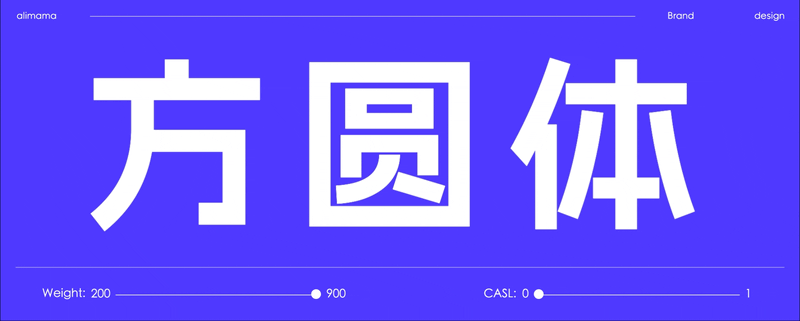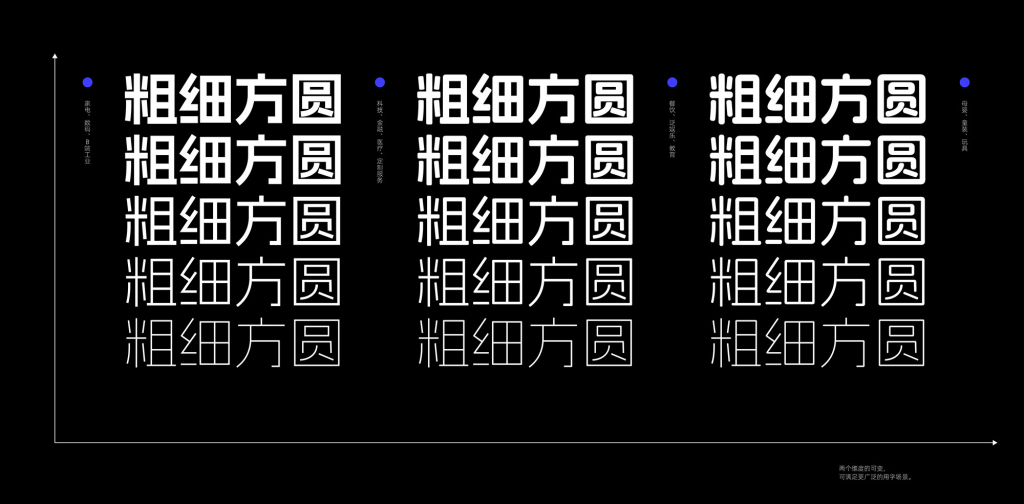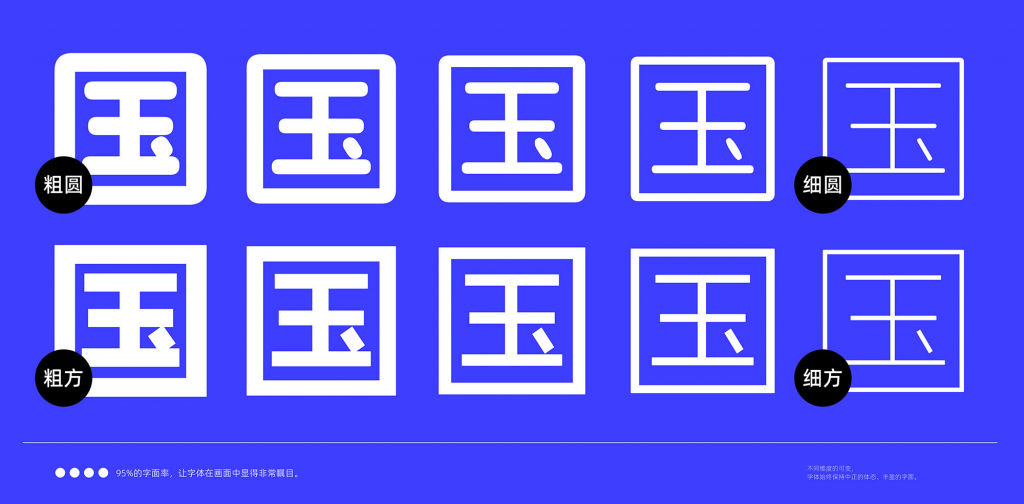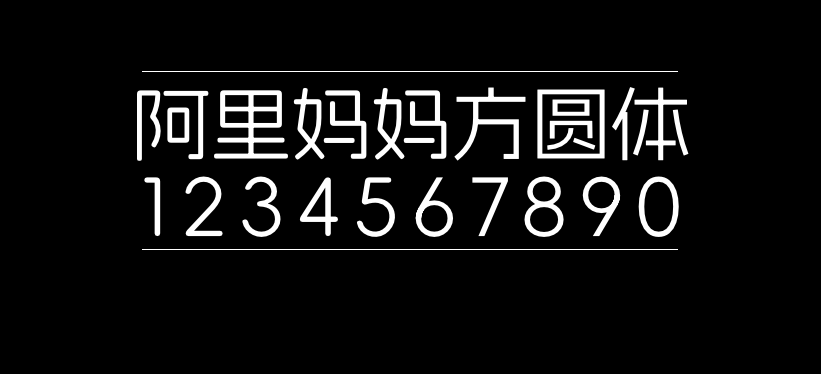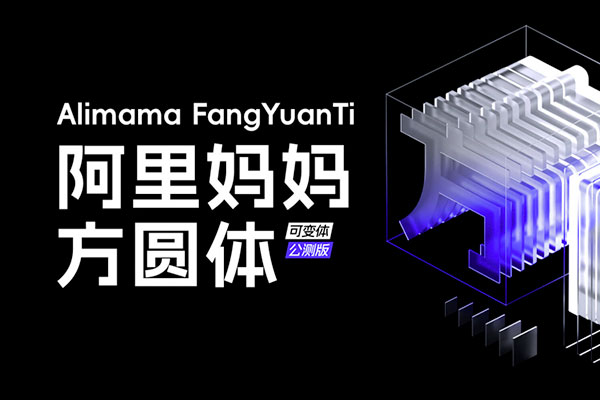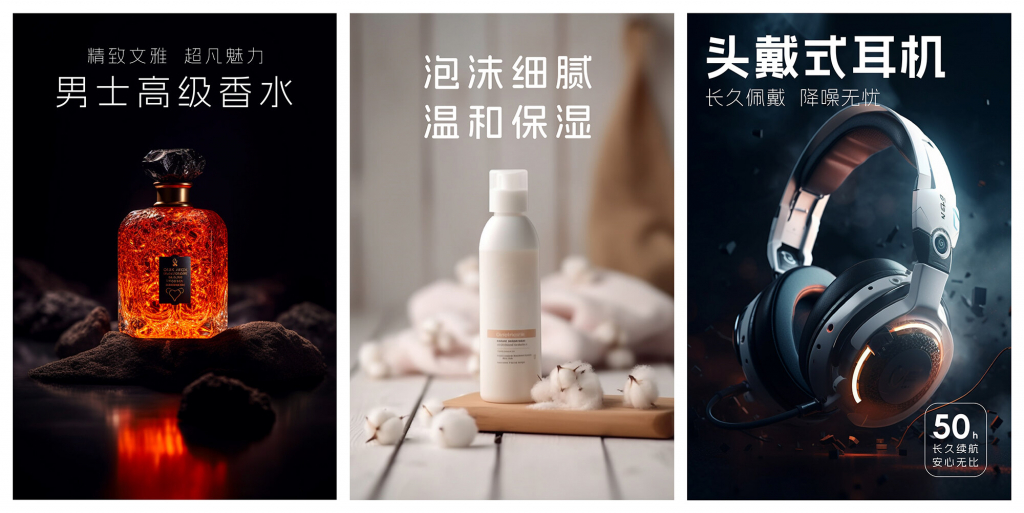
阿里妈妈方圆体
阿里妈妈方圆体是阿里旗下阿里妈妈推出的又一款免费商用字体,阿里妈妈方圆体为中文简体字库,包含字重、字型双轴可变。收纳的中文字符包括但不限于GB2312,共计6763个汉字;英文大小写(含全角、半角、合体字等)共105个;常用标点符号共175个,总计7043个字符。
设计说明:阿里妈妈方圆体包含黑体和圆体两个字型的变轴,黑体字型饱满、体态中正,布白极具现代韵律,落笔厚实而简练;字里行间流露出先锋、前卫和时尚的视觉感受,圆体字型灵动、圆润,一个字体即可覆盖多风格设计,适用于电商、广告、品牌形象、推广物料等场景。